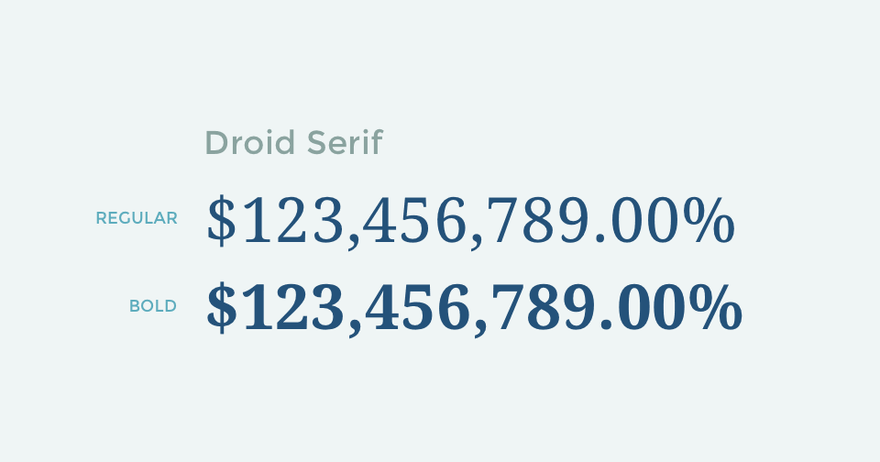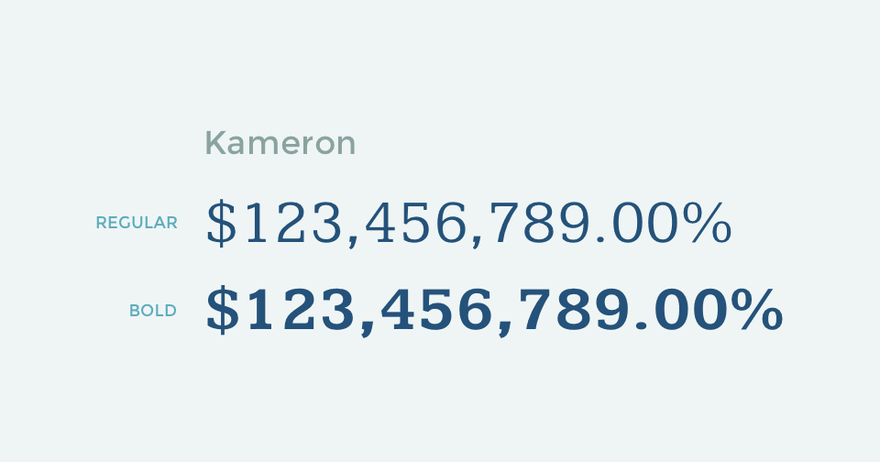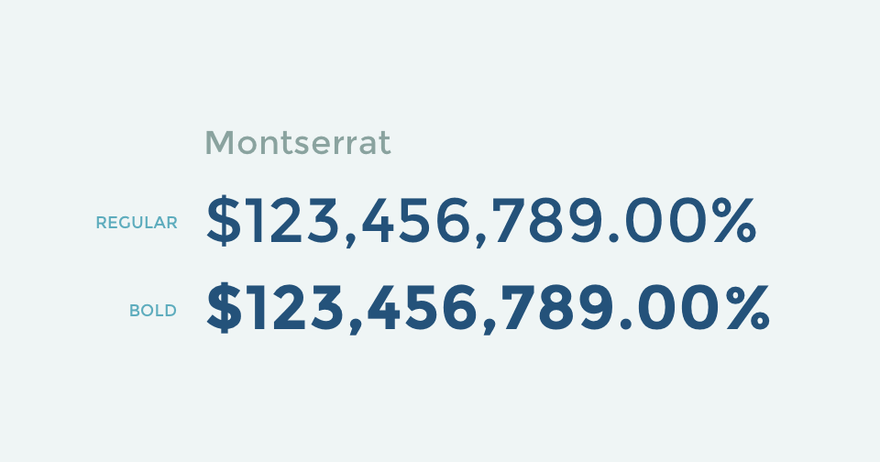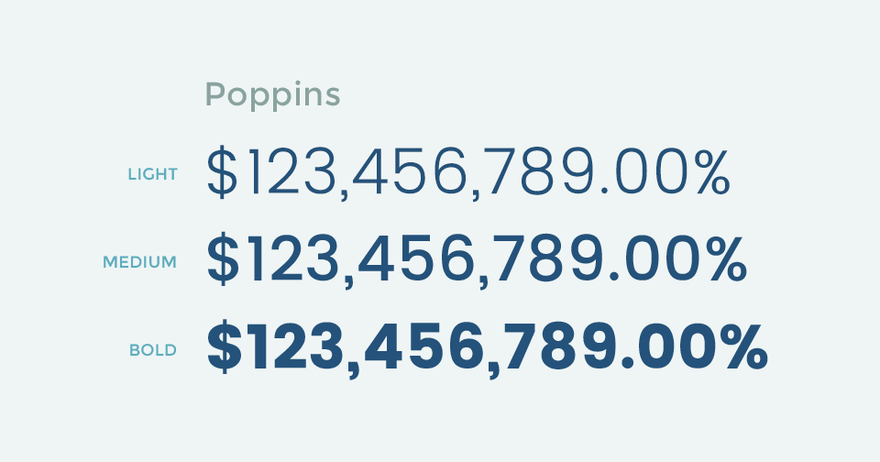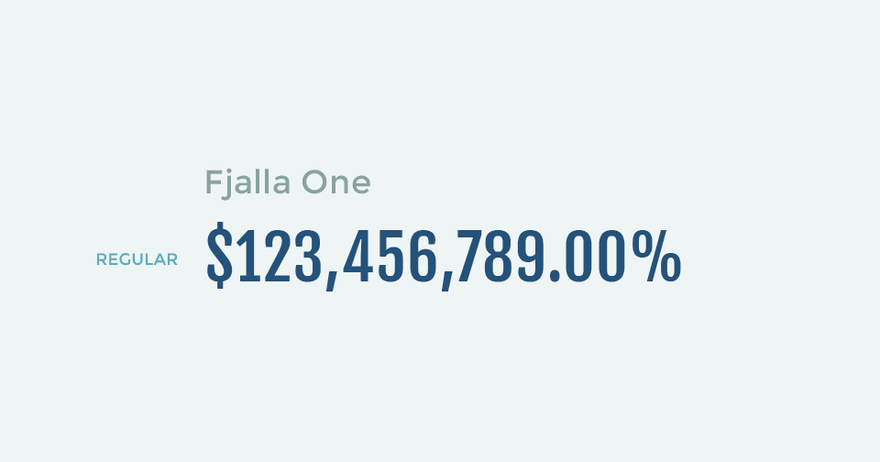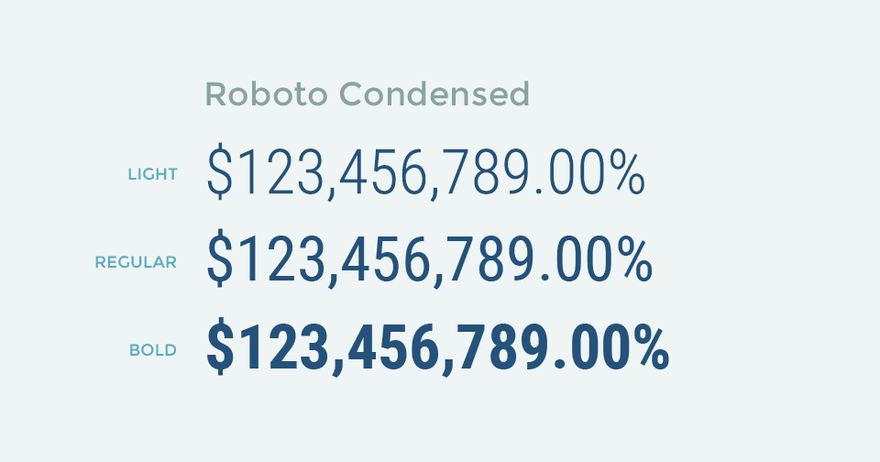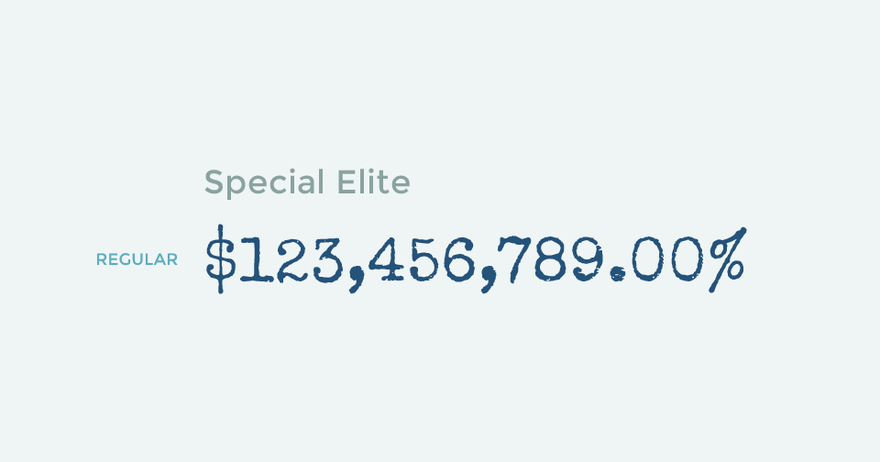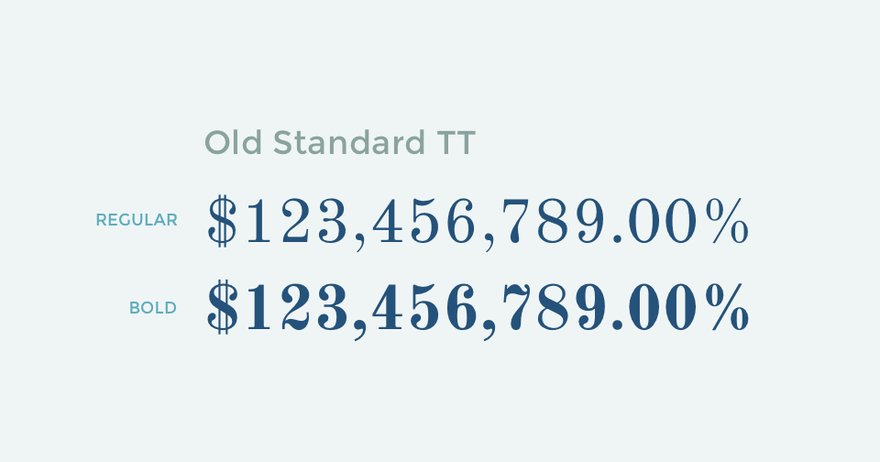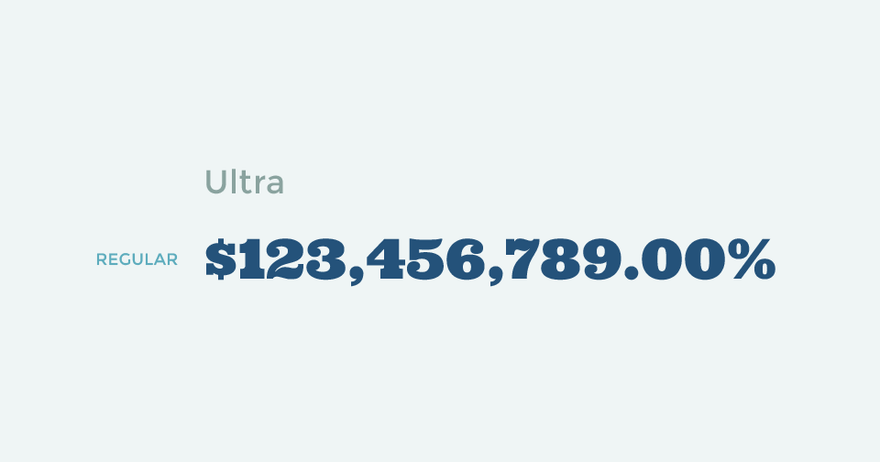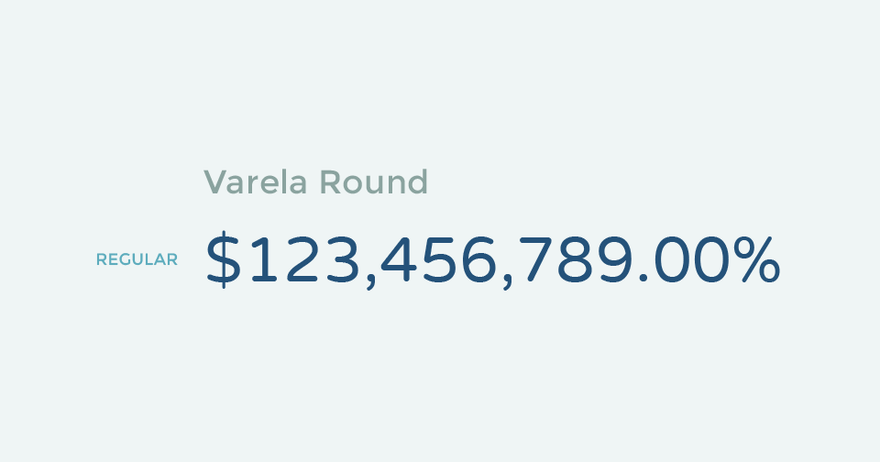
Хотя в наши дни в блогах написано бесчисленное множество публикаций и списков рекомендаций по шрифтам, не так просто найти лучшие шрифты для чисел. Для вас не так много рекомендаций, если вы не можете себе позволить FF DIN или Numbers от H&CO.
Наши принципы
Мы, в Graphiq, каждый день работаем над таблицами данных, диаграммами и инфографикой. Хотя мы используем шрифт Helvetica для большинства встраиваемых визуализаций данных, у нас есть несколько рекомендаций по выбору цифровых шрифтов, и мы рады поделиться ими с вами.
1. Равновысокие и табличные цифры
Первое правило при выборе правильного цифрового шрифта – убедиться, что он содержит равновысокие (lining) и табличные (tabular) цифры.
Термин равновысокие (маюскульные) цифры означает, что все цифры лежат на базовой линии и выровнены по высоте начальной буквы, и не имеют верхних и нижних выносных элементов (т.н. «старый стиль»).
Сверху: Libre Baskerville; снизу: Merriweather
Термин табличные цифры просто означает, что цифры являются моноширинными – каждое число занимает одно и то же горизонтальное пространство, вместо того, чтобы варьировать пространство в соответствии с собственной формой (в типографике это называется «пропорциональные» цифры).
Слева: Lato; справа: Work Sans
Табличные цифры предлагают лучшее вертикальное выравнивание, чем пропорциональные. Хотя это не обязательно для всех случаев использования, по умолчанию удобнее использовать табличные цифры.
2. Подходящие цифровые символы
Вторым шагом необходимо проверить насколько подходящие символы имеет заданный цифровой шрифт. Иногда в бесплатных шрифтах отдельные символы могут оказаться непредсказуемыми.
Например, символы «$» и «%» могут вас удивить, если вы не проверите их заранее:
Мы всегда проверяем символы «%» и «$», поэтому наша строка тестирования выглядит так: $ 123 456 789,00%. Добавьте другие символы, если они нужны для вашего набора данных.
3. Проверьте дизайн каждой цифры
Наконец, прежде чем выбрать шрифт, дважды проверьте дизайн всех его цифр – убедитесь, что цифра «один» не похожа на «семь», а «пять» не похожа на «шесть» и т. д.
Вот несколько примеров запутанных цифр со странным дизайном:
Это особые случаи, и эти шрифты, вероятно, не предназначены для использования в качестве цифровых, но это хорошие примеры, демонстрирующие важность проверки каждой отдельной цифры.
Рекомендации по шрифтам Google
Помня об этих трех принципах, мы просмотрели всю библиотеку шрифтов Google и выбрали пять лучших цифровых шрифтов в каждой категории.
Шрифты с засечками
Мы начинаем рекомендации со шрифтов с засечками. В целом, существует множество различных стилей подобных шрифтов, и мы постарались выбрать лучшие для каждого стиля.
1. Droid Serif
Droid Serif предельно прост. Типичный, хороший, современный шрифт с засечками и красивыми цифрами. Он не добавит вашему проекту слишком много блеска, но он универсален и его чрезвычайно легко читать на любом экране.
Если вам доводилось использовать PT Sans или Source Sans Pro, PT Serif и Source Serif Pro – это два других универсальных шрифта с засечками, имеющих хороший дизайн цифр.
2. Crimson Text
Размер шрифта строк с полужирным и жирным шрифтом немного уменьшен, иначе они были бы слишком длинными
Crimson Text – это то, что нужно для шрифтов с засечками в стиле Garamond. Это широко используемый шрифт с засечками, имеющий, как равновысокие, так и табличные цифры. Они прекрасно вписываются в этот стиль.
3. Old Standard TT
Если вы ищете классический, элегантный стиль, Old Standard TT – то, что нужно. С двойной вертикальной линией на знаке доллара и красивой волнистой линией в цифрах «2» и «7» он, безусловно, вызывает ощущение олдскула.
4. Kameron
Kameron может быть не так хорошо известен, как перечисленные ранее шрифты, но у него хорошие цифры с засечками и они шире, чем у большинства шрифтов с засечками. Это хороший цифровой шрифт, который следует иметь в своей коллекции.
5. Copse
Опять же, не самый известный шрифт с засечками, имеющий уникальные свойства. Низкоконтрастный дизайн придает ему твердость. Кроме того, он очень читабельный даже при небольших размерах шрифта.
Рубленые (гротесковые) шрифты
В категории рубленых шрифтов есть много отличных системных шрифтов интерфейса. Здесь представлены два лучших, на наш взгляд, шрифта, а три других следует отметить за их уникальные стили.
1. Open Sans
У этого шрифта больше вариантов веса, чем показано на этом изображении
В настоящее время Open Sans является самым популярным шрифтом Google. Многие могут утверждать, что он скучный и станет таким же клише, как Helvetica, но это хороший универсальный рубленый шрифт с красивыми цифрами. Если вы уже используете Open Sans, используйте его для чисел.
2. Lato
У этого шрифта больше вариантов веса, чем показано на этом изображении
Еще один широко распространенный рубленый шрифт. Он сильно отличается стилем от Open Sans, благодаря более низкому контрасту и поперечной черте в основании цифры «1», но при этом он довольно универсален.
3. Roboto Condensed
У этого шрифта больше вариантов веса, чем показано на этом изображении
Размышляя о цифровых шрифтах с засечками, некоторые из вас, возможно, захотят использовать Oswald из-за его сильного, сжатого стиля. К сожалению, Oswald содержит пропорциональные числа и не подойдет в тех случаях, когда вам нужно вертикальное выравнивание. Roboto Condensed – лучшая табличная альтернатива, которую мы нашли.
4. Titillium Web
У этого шрифта больше вариантов веса, чем показано на этом изображении
Titillium Web имеет уникальный стиль. Он квадратный и кажется суровым. Если вы хотите, чтобы стиль передавал холодную суровую правду, Titillium может оказаться хорошим выбором.
5. Varela Round
Varela Round – это полная противоположность предыдущему шрифту. Он очень круглый и милый. Если вы хотите сделать цифры более дружелюбными или соответствующими вашей отрасли, Varela Round – отличный выбор.
Кроме того, стоит упомянуть, что Varela Round часто используется как облегченная версия Montserrat, очень популярного рубленого шрифта. Поскольку в Montserrat нет табличных цифр, Varela Round (или Varela) отлично подойдет для этой задачи.
Экранные шрифты
Рассмотренные выше рубленые шрифты и шрифты с засечками пригодятся, когда вы создаете таблицу данных или информационную панель. Но, когда вы создаете инфографику и плакаты с огромными числами вам нужны шрифты с сильно выраженной индивидуальностью. Поэтому ниже представлен список рекомендуемых экранных шрифтов.
1. Graduate
Graduate содержит красивые цифры с выравниванием по левому краю. Он идеально подходит для инфографики, связанной с образованием, спортом и просто для цифровых дисплеев.
2. Changa One
Changa One дает вам сильные полужирные табличные цифры. Он менее формален, чем жирные рубленные шрифты, и может пригодиться для развлекательной инфографики и плакатов.
3. Special Elite
Вы не поверите, но этот рукописный шрифт на самом деле содержит табличные цифры. Он идеально подходит для ностальгических дизайнов или даже перечисления чего-то таинственного, например, числа совершенных убийств в тексте о преступнике. Это очень уникальный шрифт, который можно использовать несколькими способами.
4. Stardos Stencil
Прекрасный трафаретный шрифт для всего хипстерского, и дизайнов на обёрточной бумаге.
5. Iceland
Iceland – это квадратный современный геометрический шрифт, отлично подходящий для технологических и механических данных. Если вам нужен более высокий шрифт выберите Iceberg – еще один отличный шрифт от того же дизайнера.
Пропорциональные шрифты
Наконец, есть несколько отличных шрифтов с красиво оформленными цифрами. Единственная их проблема заключается в том, что они не являются табличными. Если вы не слишком озабочены вертикальным выравниванием чисел, тогда они могут стать отличным выбором.
1. Montserrat
Список рекомендаций по шрифтам от Google не будет полным без Montserrat. Он имеет изящные цифры. (Эх, если бы они были табличными!)
2. Poppins
У этого шрифта больше вариантов веса, чем показано на этом изображении
Еще один широко используемый рубленый шрифт Poppins также имеет великолепный дизайн цифр. Цифра «9» немного нескладная, но в целом это отличный шрифт, у которого больше вариантов веса, чем у Montserrat.
3. Bitter
Bitter – шрифт с засечками. Это отличный титульный шрифт с большими цифрами. Как и Montserrat с Poppins, Bitter широко используется во всем мире, и вам определенно следует подумать об использовании его цифр, если вы уже используете его.
4. Ultra
Ultra – это жирный шрифт. Если бы у него были табличные цифры, у Changa One не было бы шансов. Если вы ищете шрифт для больших чисел, например, заголовок плаката, Ultra – отличный выбор.
5. Fjalla One
Мы много думали над тем, стоит ли нам включать в наш список Oswald, потому что многие используют его в качестве сжатого жирного цифрового шрифта и, возможно, как бесплатную альтернативу FF Din. Тем не менее, время от времени знак доллара и цифра «4» в шрифте Oswald выглядят противоречиво. Поэтому мы представляем Fjalla One, как альтернативу с более сбалансированными цифрами.
Вот и все. Вы ознакомились с нашими тремя принципами выбора лучших шрифтов для чисел и визуализации данных, и 20 отличными бесплатными шрифтами от Google для отображения чисел. Надеюсь, эта статья была полезной! Чем вы руководствуетесь в выборе шрифтов для чисел?